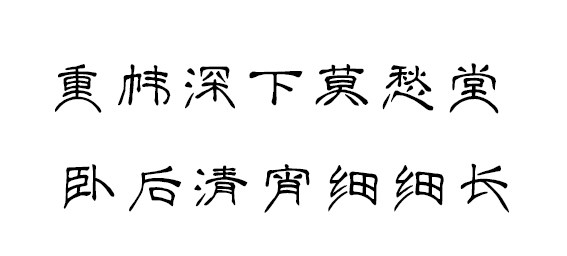
莫愁体——一款莫愁前路无知己,天下谁人不识君的创意字体
字体简介:这是一款特别有意思的创意字体,所有字体最下面的横笔画向上弯曲,看起来像一个难过的表情,整体营造出一种不开心的氛围;然而字体的初衷却是表现了一个乐观者的自嘲,也许外面表现的是难过,但内心永远保持一份乐观的心态。
莫愁体
字体名称:莫愁体
字体分类:创意字体
使用场景:影视  广告海报